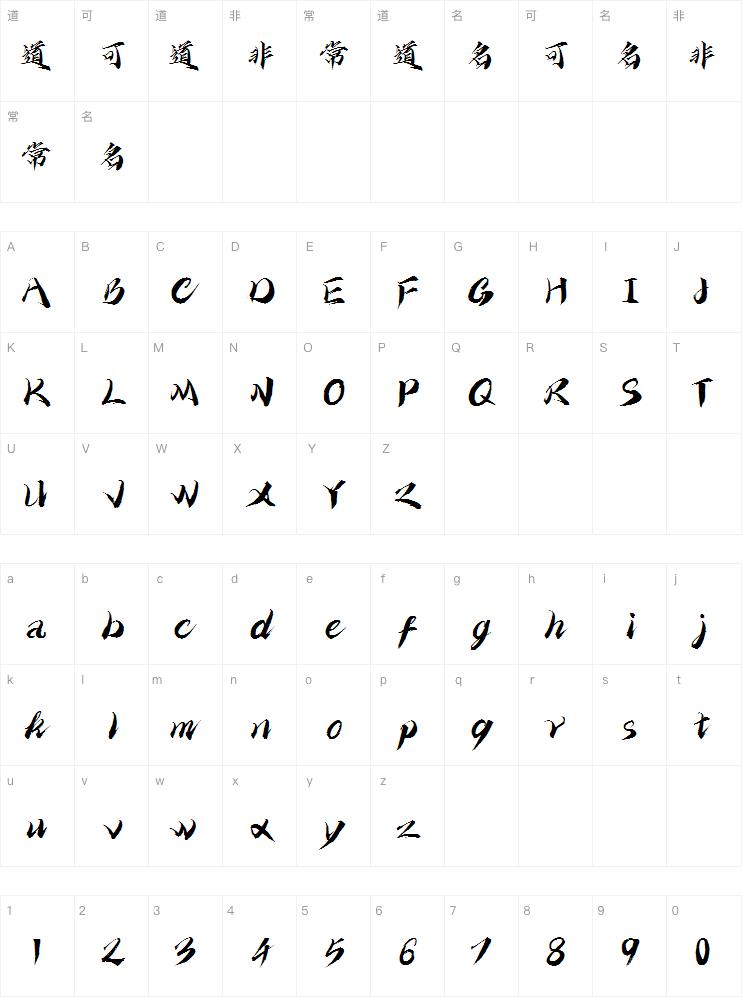
字嶼雲遊手書tc
字嶼雲遊手書 / Fontprime - 這是一款以毛筆字風格為基底,更為強調字體筆畫的曲折收放變化的創意手書。 簡介 - 「字嶼雲遊手書」整體字勢開合揖讓得宜,騰挪轉折間,不致過於纖秀婉約,婉轉中猶見鏗鏘力道,鋒芒盡顯。透過局部形變與筆勢外拓,疊加出整體氣勢,兼顧陰柔與陽剛、含蓄與強勁之美。露鋒用筆貫穿字體始終,結體緊緻,大量曲線更強化字勢動感與字形張力,恰似流雲縈繞劍鋒,飄逸中蘊藏銳勁 。 - 以台語常用標准漢字為標准,參考jf7000字集,包括註音符號、歐文字符、阿拉伯數字和標點符號,總字符約7640字以上。 - 字嶼雲遊手書採開放授權規則:無需向作者申請、支付費用,也不用標註字型出處,不論個人創作或商業用途,都能自由使用。並可將字型檔案分享他人,或安裝在任何軟體、硬體設備裡 。 我們希望這款字有無限的可能性: - 國潮文創:手帳封面題字、刺繡吊飾文字 - 台式茶飲與伴手禮:珍珠奶茶杯身題字、鳳梨酥禮盒側邊文案 - 出版領域:鄉土神話故事集、山林散文選的封面與章節標題 - 影視動畫:仙俠劇開場片名、廟宇場景牌匾題字 - 戶外廣告:古蹟園區導覽牌、文創商圈燈箱 - 傳統服飾:廟會常見的服飾刺繡文字、改良旗袍腰帶印字 - 文博展覽:特展海報、老街文物說明卡 - 品牌識別:中藥行招牌、台式茶館 logo - 工藝飾品:陶瓷茶具底款、珊瑚吊墜刻字 这是一款免费可商用字体,如果需要联系版权,可联系邮箱:social@fontprime.com